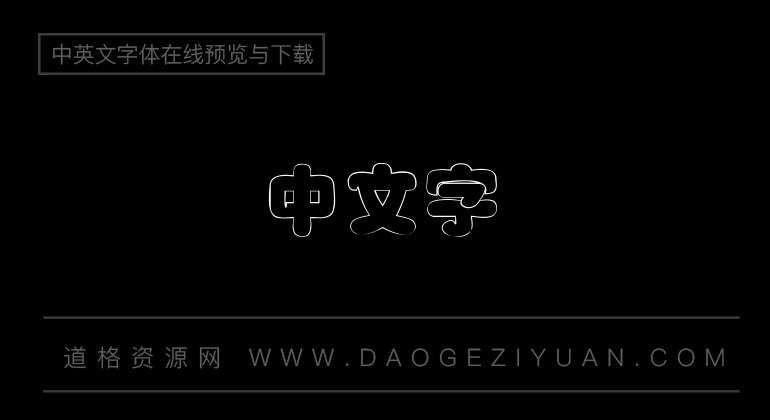
金梅疊圓空心國際碼字體是一種擁有獨特設計的國際碼字體。它擁有一種結合了圓形和空心等特性的複雜設計,讓字體看起來更加有趣,也更加突出。在金梅疊圓空心國際碼字體中,每個字母都有一個圓形的框架,裡面是空心的,使得字體看起來更加精緻,也更加突出。這種字體可以用於標識、標誌、招牌等各種設計中,讓設計更加精美、時尚。內容介紹
金梅疊圓空心國際碼字體是一款非常不錯的手寫藝術字體,具有很好的視覺感,適合於文化類的宣傳設計、商業類品牌的廣告和產品包裝設計以及個性化文字排版等較多場景。